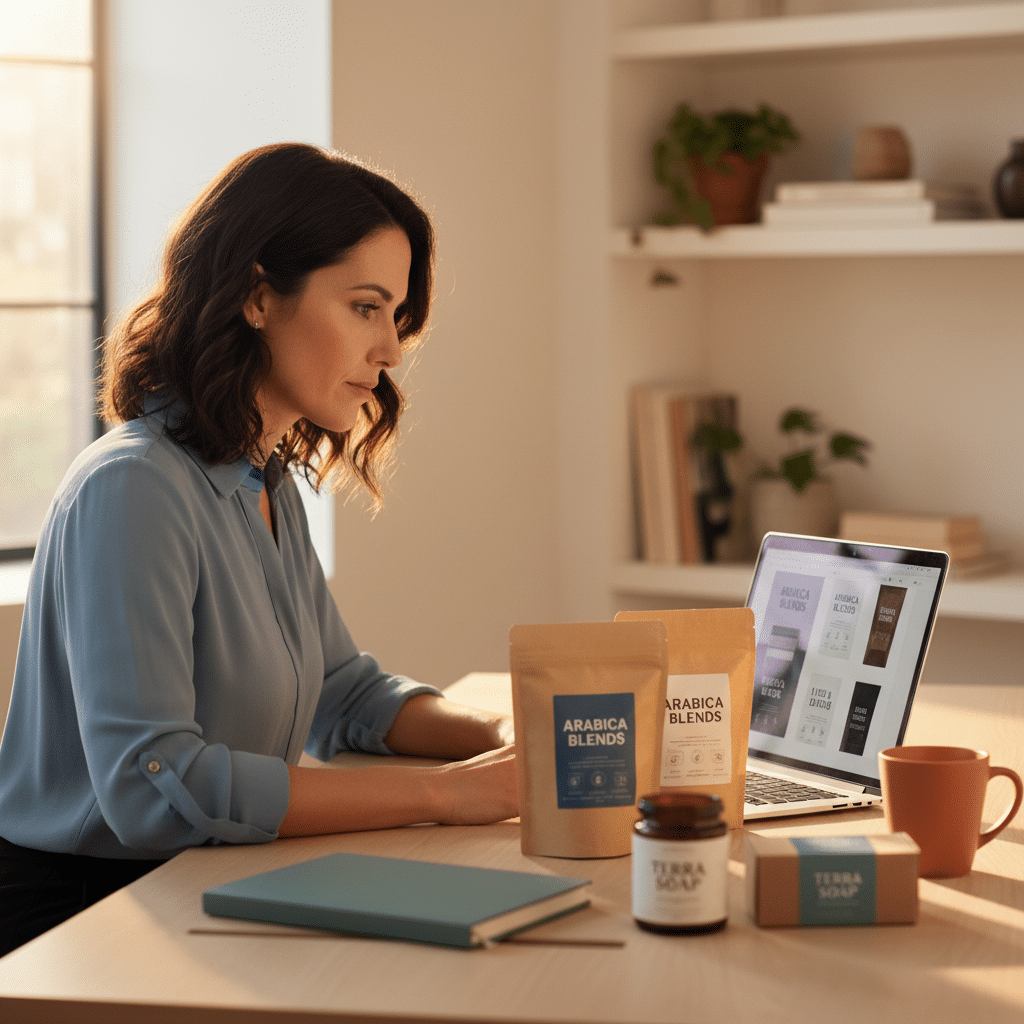
ฟอนต์เปลี่ยนแบรนด์! เลือกฟอนต์ยังไงให้ลูกค้าจำได้
การออกแบบอัตลักษณ์แบรนด์ให้เป็นที่จดจำนั้นมีองค์ประกอบหลายส่วน และหนึ่งในหัวใจสำคัญที่มักถูกมองข้ามคือการเลือกใช้ตัวอักษรหรือฟอนต์ การเรียนรู้เรื่อง ฟอนต์เปลี่ยนแบรนด์! เลือกฟอนต์ยังไงให้ลูกค้าจำได้ จึงเป็นทักษะที่จำเป็นสำหรับผู้ประกอบการและนักการตลาด เพราะฟอนต์ไม่ใช่แค่เครื่องมือในการแสดงข้อความ แต่เป็นองค์ประกอบเชิงกลยุทธ์ที่สามารถสื่อสารบุคลิกภาพ ค่านิยม และสร้างความแตกต่างให้กับแบรนด์ได้อย่างทรงพลัง การเลือกฟอนต์ที่เหมาะสมจะช่วยยกระดับการรับรู้ของลูกค้า สร้างความน่าเชื่อถือ และทำให้แบรนด์โดดเด่นในตลาดที่มีการแข่งขันสูง
ประเด็นสำคัญของการเลือกฟอนต์
- สื่อสารบุคลิกแบรนด์: ฟอนต์ทำหน้าที่เป็น “เสียง” ของแบรนด์ สามารถสื่อถึงความหรูหรา (Serif) หรือความทันสมัย (Sans Serif) ได้โดยไม่ต้องใช้คำพูด
- ความอ่านง่ายคือหัวใจ: ฟอนต์ที่ดีต้องชัดเจนและอ่านง่ายในทุกขนาดและทุกแพลตฟอร์ม ตั้งแต่ฉลากสินค้าขนาดเล็กไปจนถึงป้ายโฆษณาขนาดใหญ่
- จิตวิทยามีผลต่อการรับรู้: การเลือกฟอนต์ต้องสอดคล้องกับกลุ่มเป้าหมาย โดยคำนึงถึงจิตวิทยาของฟอนต์ที่สามารถกระตุ้นอารมณ์และการตัดสินใจของลูกค้าได้
- ความสอดคล้องสร้างการจดจำ: การใช้ฟอนต์หลักเพียง 1-2 รูปแบบที่เข้ากัน (Font Pairing) อย่างสม่ำเสมอในทุกสื่อ จะช่วยสร้างภาพจำที่แข็งแกร่งและเป็นเอกภาพ
- ฟอนต์เป็นเครื่องมือในการ Rebranding: การปรับเปลี่ยนฟอนต์เป็นกลยุทธ์สำคัญในการปรับภาพลักษณ์แบรนด์ให้สดใหม่และเข้าถึงกลุ่มเป้าหมายใหม่ๆ
ความสำคัญของฟอนต์ต่อการสร้างแบรนด์
ในโลกของการสร้างแบรนด์ (Branding) ทุกองค์ประกอบภาพล้วนมีความสำคัญ ตั้งแต่โลโก้ สี ไปจนถึงการออกแบบบรรจุภัณฑ์ แต่มีสิ่งหนึ่งที่ทำงานเงียบๆ ทว่าส่งผลกระทบอย่างมหาศาลต่อการรับรู้ของผู้บริโภค นั่นคือ “ฟอนต์” (Font) หรือที่เรียกในเชิงเทคนิคว่า “ไทโปกราฟี” (Typography) ฟอนต์เป็นมากกว่าแค่ตัวอักษรที่เรียงกันเป็นคำ แต่เป็นเครื่องมือสื่อสารที่ทรงพลังในการสร้างอัตลักษณ์และบุคลิกภาพให้กับแบรนด์ การเลือกฟอนต์ที่ถูกต้องสามารถเปลี่ยนการรับรู้ของลูกค้าที่มีต่อผลิตภัณฑ์หรือบริการได้อย่างสิ้นเชิง
ฟอนต์คือ ‘เสียง’ ที่มองเห็นได้ของแบรนด์
หากแบรนด์สามารถพูดได้ ฟอนต์ก็คือ “น้ำเสียง” ที่ใช้ในการสื่อสาร ฟอนต์แต่ละแบบมีบุคลิกเฉพาะตัวที่สามารถกระตุ้นอารมณ์และความรู้สึกที่แตกต่างกันได้ ตัวอย่างเช่น ฟอนต์ที่มีลักษณะโค้งมนอาจให้ความรู้สึกเป็นมิตรและเข้าถึงง่าย ในขณะที่ฟอนต์ที่มีเส้นสายเฉียบคมและเป็นเหลี่ยมมุมอาจสื่อถึงความแข็งแกร่ง นวัตกรรม และความเป็นมืออาชีพ ดังนั้น การเลือกฟอนต์จึงเปรียบเสมือนการเลือกวิธีที่แบรนด์จะ “พูดคุย” กับลูกค้า ซึ่งเป็นด่านแรกในการสร้างความสัมพันธ์และความประทับใจ
สร้างความน่าเชื่อถือและยกระดับภาพลักษณ์
การเลือกใช้ฟอนต์ที่เหมาะสมช่วยเสริมสร้างความน่าเชื่อถือและความเป็นมืออาชีพให้กับแบรนด์ได้เป็นอย่างดี ลองนึกภาพสถาบันการเงินที่ใช้ฟอนต์ลายมือแบบเด็กๆ หรือแบรนด์สินค้าสำหรับเด็กที่ใช้ฟอนต์แบบทางการและเคร่งขรึม ย่อมทำให้เกิดความรู้สึกขัดแย้งและลดทอนความน่าเชื่อถือลง ในทางกลับกัน แบรนด์แฟชั่นระดับสูงมักเลือกใช้ฟอนต์กลุ่ม Serif ที่มีความสง่างามเพื่อสะท้อนถึงคุณภาพและความหรูหรา ในขณะที่บริษัทเทคโนโลยีมักเลือกใช้ฟอนต์ Sans Serif ที่ดูสะอาดตาเพื่อสื่อถึงความทันสมัยและนวัตกรรม การเลือกฟอนต์ที่สอดคล้องกับอุตสาหกรรมและภาพลักษณ์ที่ต้องการจะช่วยยกระดับแบรนด์ให้ดูพรีเมียมและน่าไว้วางใจในสายตาของผู้บริโภค
เอกลักษณ์ที่แตกต่างและป้องกันการลอกเลียน
ในตลาดที่มีการแข่งขันสูง การสร้างความแตกต่างเป็นสิ่งสำคัญอย่างยิ่ง ฟอนต์เป็นหนึ่งในเครื่องมือที่ช่วยให้แบรนด์โดดเด่นและเป็นที่จดจำได้ง่ายขึ้น แบรนด์ระดับโลกหลายแห่งลงทุนในการสร้างฟอนต์เฉพาะ (Custom Font) ของตัวเองขึ้นมาเพื่อใช้ในทุกการสื่อสาร ตั้งแต่โลโก้ไปจนถึงสื่อโฆษณา การมีฟอนต์ที่เป็นเอกลักษณ์ไม่เพียงแต่ช่วยเสริมสร้างอัตลักษณ์ที่แข็งแกร่ง แต่ยังเป็นเกราะป้องกันการลอกเลียนแบบจากคู่แข่ง ทำให้ลูกค้าสามารถจดจำและแยกแยะแบรนด์ได้ทันทีที่เห็น แม้จะยังไม่ได้อ่านข้อความทั้งหมดก็ตาม
รู้จักประเภทฟอนต์หลัก: Serif และ Sans Serif
การทำความเข้าใจประเภทของฟอนต์เป็นขั้นตอนพื้นฐานที่สำคัญที่สุดในการเลือกฟอนต์ให้เหมาะสมกับแบรนด์ โดยทั่วไปแล้ว ฟอนต์สามารถแบ่งออกได้เป็นสองกลุ่มหลักคือ Serif และ Sans Serif ซึ่งแต่ละกลุ่มมีลักษณะเด่นและสื่ออารมณ์ที่แตกต่างกันอย่างชัดเจน การเลือกใช้ระหว่างสองประเภทนี้ขึ้นอยู่กับบุคลิกของแบรนด์และข้อความที่ต้องการสื่อสารไปยังกลุ่มเป้าหมาย
ฟอนต์ไม่ใช่แค่ตัวอักษร แต่คือเสียงที่มองเห็นได้ซึ่งบอกเล่าเรื่องราวและบุคลิกของแบรนด์ การเลือกที่ถูกต้องสามารถสร้างความไว้วางใจและทำให้แบรนด์เป็นที่จดจำได้ในทันที
Serif: ความคลาสสิก สง่างาม และเป็นทางการ
ฟอนต์ประเภท Serif (อ่านว่า เซ-ริฟ) คือฟอนต์ที่มี “เชิง” หรือ “ขีดเล็กๆ” อยู่ที่ปลายของตัวอักษร เชิงเหล่านี้มีต้นกำเนิดมาจากการจารึกตัวอักษรบนหินในสมัยโรมัน ซึ่งช่วยนำสายตาและทำให้อ่านข้อความยาวๆ ในสื่อสิ่งพิมพ์ได้ง่ายขึ้น ฟอนต์ Serif มักให้ความรู้สึกที่คลาสสิก เป็นทางการ น่าเชื่อถือ และสง่างาม ด้วยเหตุนี้จึงมักถูกนำไปใช้กับแบรนด์ที่ต้องการสร้างภาพลักษณ์แห่งความหรูหรา มีประวัติศาสตร์ยาวนาน และมีความน่าไว้วางใจสูง เช่น แบรนด์แฟชั่นชั้นสูง, สถาบันการเงิน, โรงแรมหรู, สำนักพิมพ์หนังสือ หรือสำนักงานกฎหมาย
Sans Serif: ความทันสมัย เรียบง่าย และสะอาดตา
คำว่า “Sans” ในภาษาฝรั่งเศสแปลว่า “ไม่มี” ดังนั้น ฟอนต์ Sans Serif (ซานส์-เซ-ริฟ) จึงหมายถึงฟอนต์ที่ “ไม่มีเชิง” ที่ปลายตัวอักษร ทำให้มีลักษณะที่ดูเรียบง่าย สะอาดตา และทันสมัย ฟอนต์ประเภทนี้ได้รับความนิยมอย่างสูงในยุคโมเดิร์นและบนสื่อดิจิทัล เนื่องจากความเรียบง่ายของมันทำให้อ่านง่ายบนหน้าจอที่มีความละเอียดแตกต่างกัน และสื่อถึงความตรงไปตรงมา ไม่ซับซ้อน แบรนด์ที่มักเลือกใช้ฟอนต์ Sans Serif คือกลุ่มที่ต้องการสื่อสารความเป็นนวัตกรรม ความเป็นมิตร และความมินิมอล เช่น บริษัทเทคโนโลยี, สตาร์ทอัพ, แบรนด์สินค้าไลฟ์สไตล์สมัยใหม่ หรือแบรนด์ที่เน้นการออกแบบที่สะอาดตา